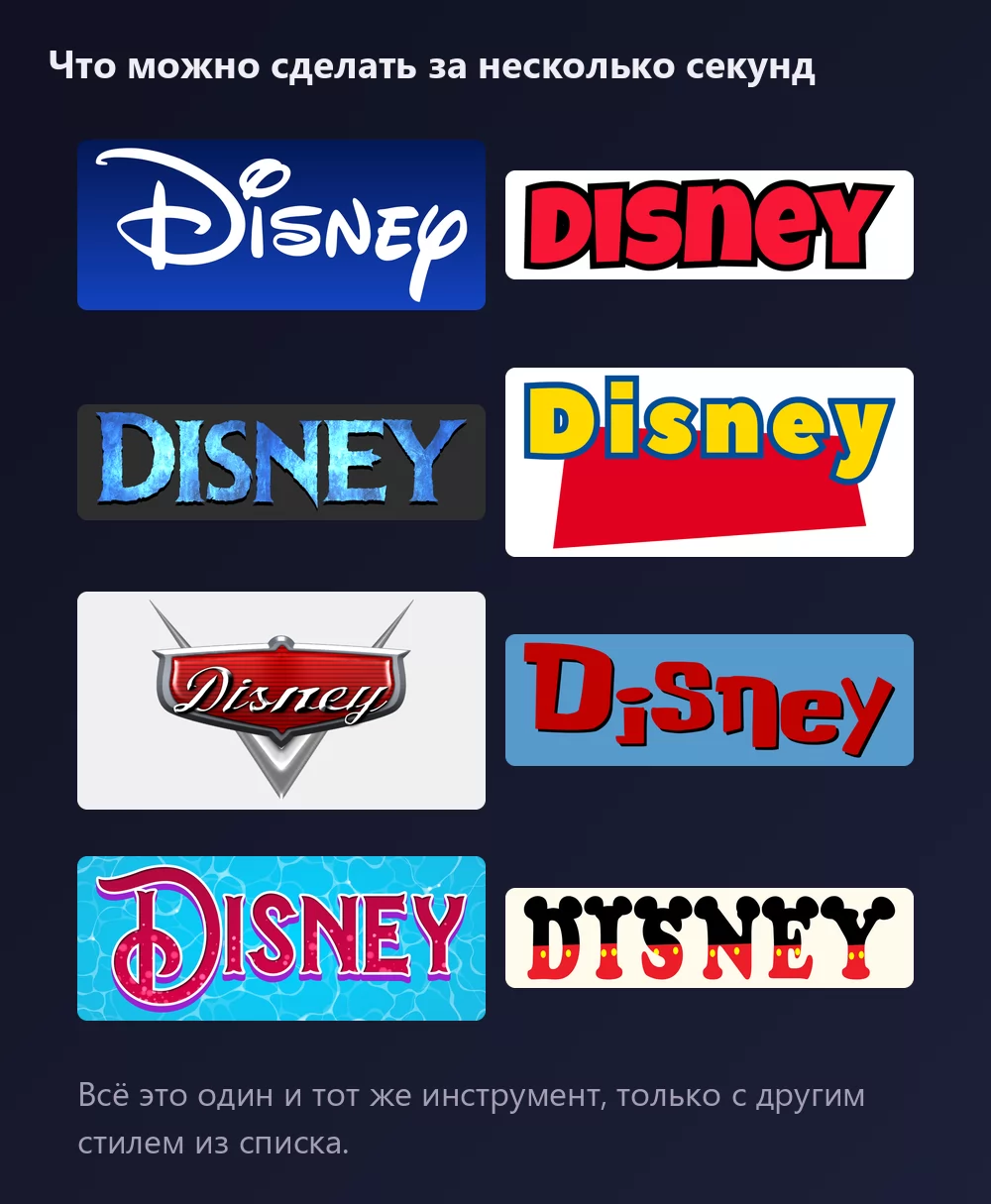
О шрифте Disney
Компания The Walt Disney Company была основана в 1923 году братьями Уолтом и Роем О. Диснеем и выросла в одну из крупнейших медиакомпаний мира. Микки Маус, её самый известный персонаж, является официальным талисманом.
Надпись в логотипе это стилизованная версия подписи Уолта Диснея. Она служит корпоративным логотипом с 1956 года и никогда не выпускалась как шрифт: официального файла для установки не существует. Вместо него все скачивают Waltograph, шрифт, который Джастин Каллаган нарисовал по образцу логотипа. У него две версии: Waltograph 42, с прописными и строчными буквами, несколькими лигатурами и альтернативными знаками, и Waltograph UI, одноразмерный вариант, сделанный так, чтобы оставаться читаемым в мелком кегле и на экране. Обе бесплатны для личного использования.
Как сделать текст в стиле Disney
Откройте генератор и замените пример своим текстом: имя ребёнка, название праздника, фамилия для футболки в поездку. Буквы перерисовываются прямо во время набора. Оставьте обычный регистр: стиль подписи это рукописный шрифт, и слово прописными теряет высокую петлю D, по которой узнают Disney.
Классика это белая подпись на ярко-синем градиенте. На вкладке «Стили» заливка, обводка и тень меняются отдельно, так что форму букв можно оставить, а цвета увести в другую сторону: золото на тёмно-синем для свадьбы, розовый для праздника принцесс.
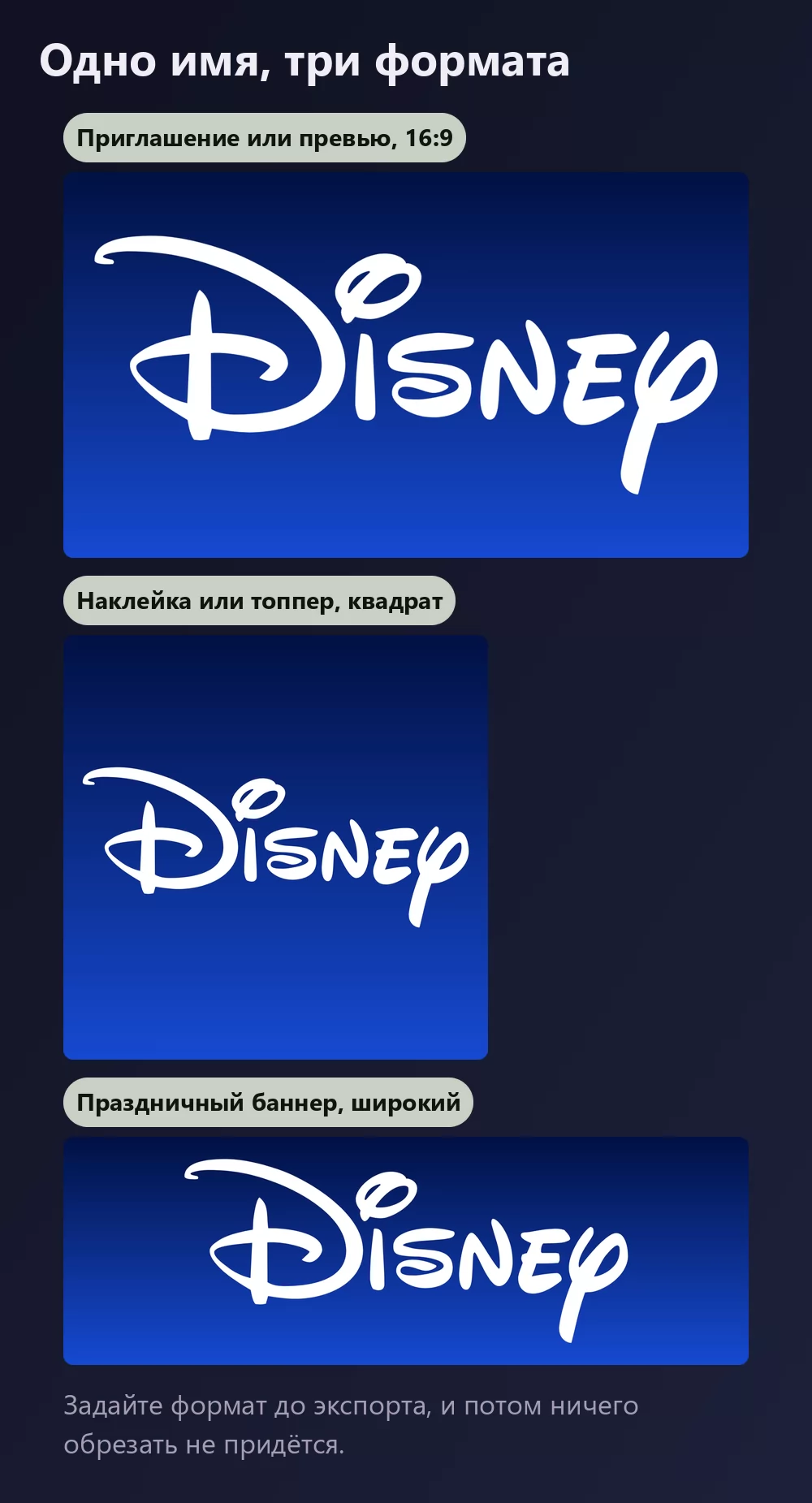
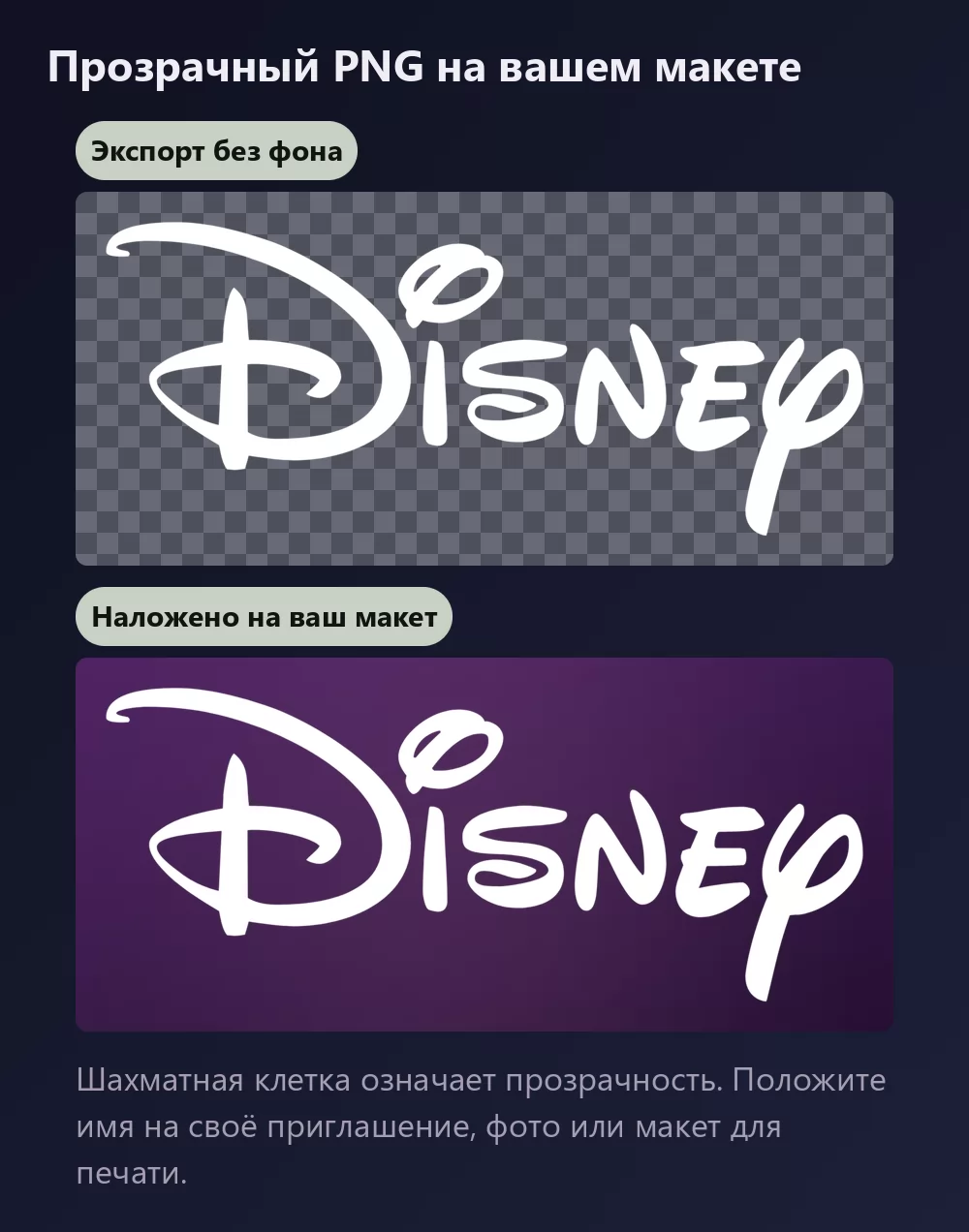
Длинные имена быстро заполняют ширину
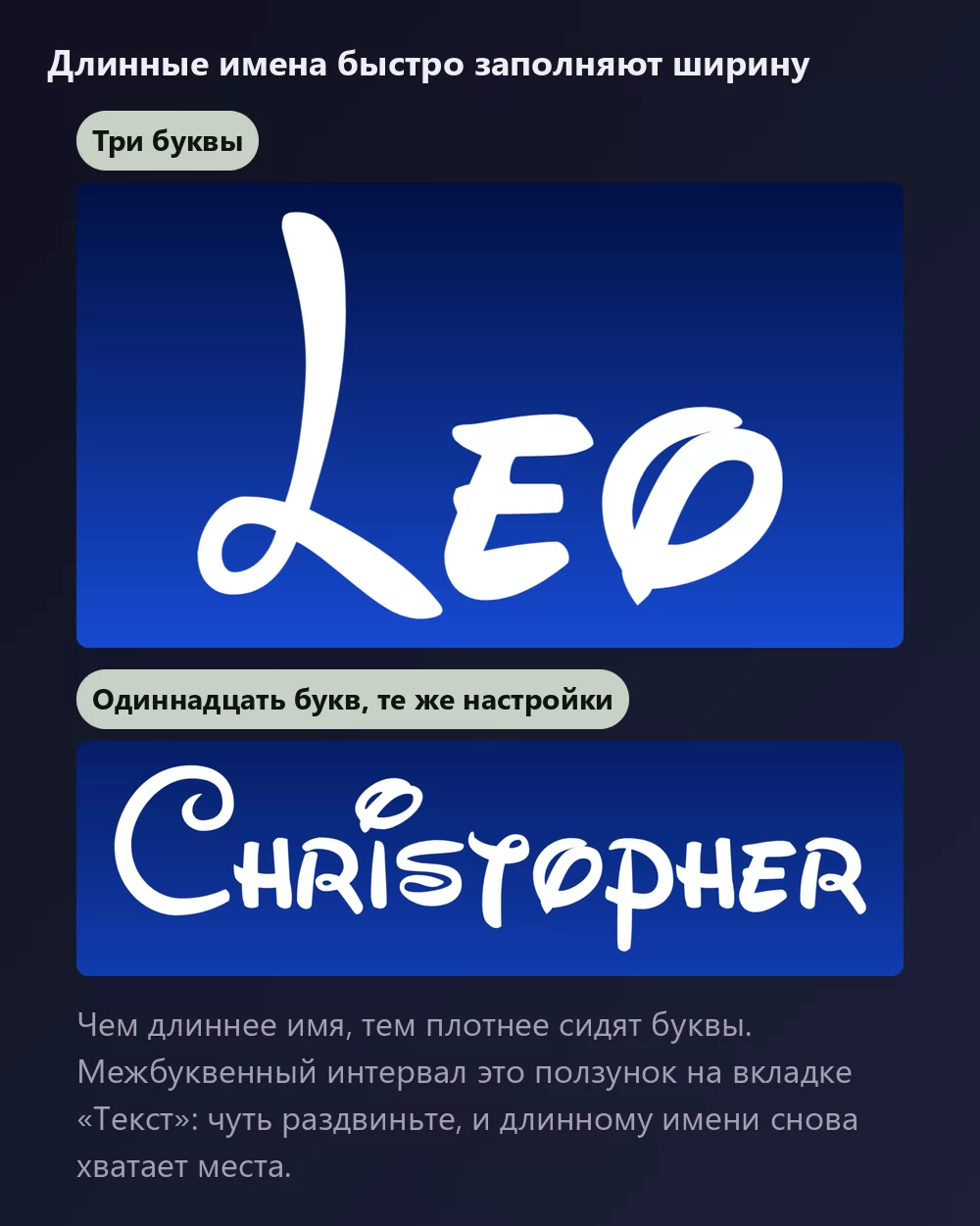
Чем больше букв, тем плотнее они сидят. Межбуквенный интервал это ползунок на вкладке «Текст»: чуть раздвиньте, и длинное имя перестанет выглядеть сжатым. На той же вкладке масштаб, межстрочный интервал, изгиб и поворот.
Стиль подписи или стиль Микки
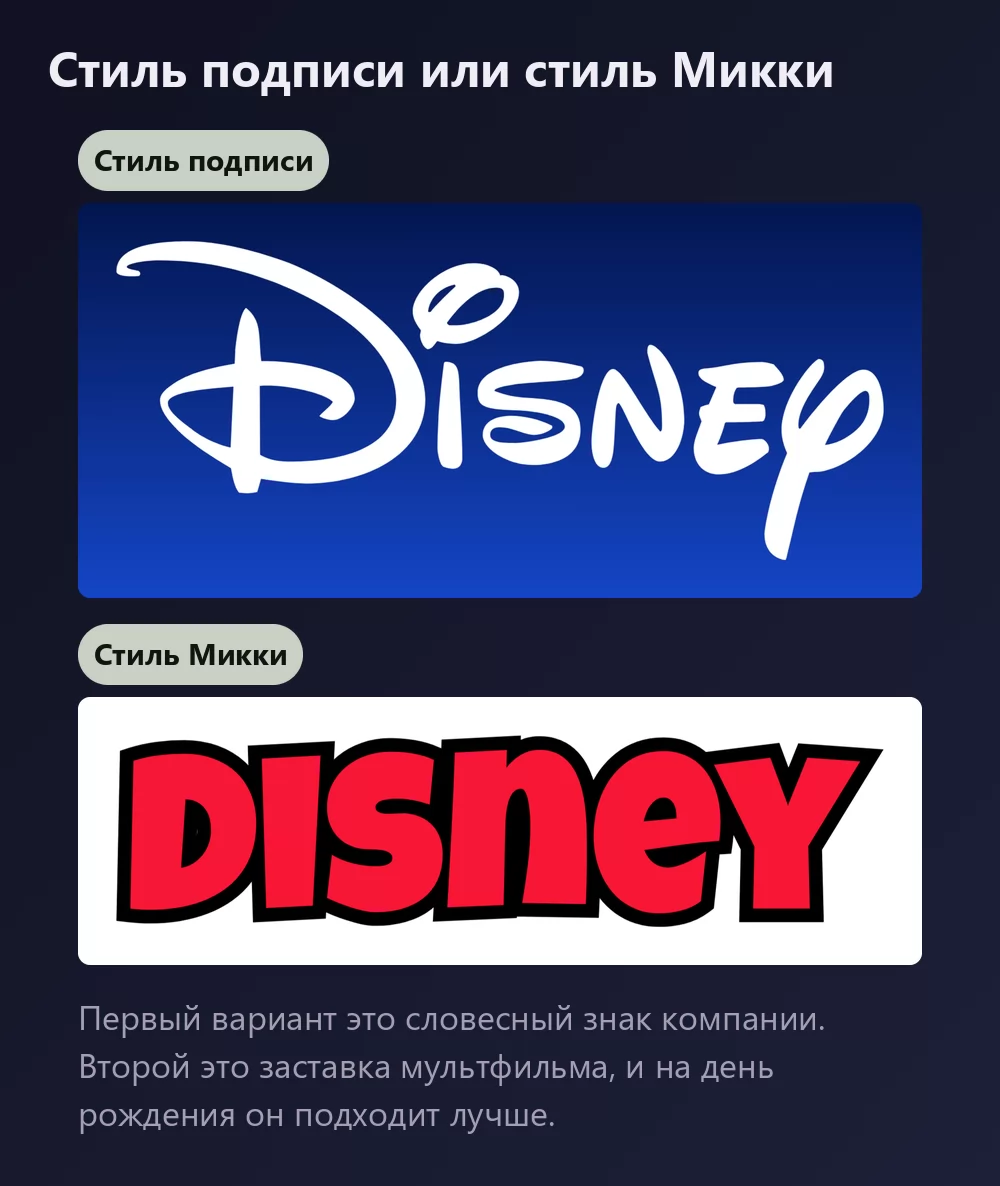
Стиль подписи это словесный знак компании: плавная рукописная надпись с высокой петлёй D, белым на синем. Именно это большинство представляет, говоря «шрифт Disney».
Стиль Микки это заставка мультфильма: жирные красные прописные с чёрной обводкой, надпись из короткометражек о Микки Маусе. В нём нет корпоративной символики, он читается с другого конца комнаты, и для первого дня рождения обычно подходит лучше подписи. В генераторе шрифта Микки Маус он есть как готовый стиль.
Какой шрифт, если вы хотите его установить
Сам логотип это не шрифт. Это леттеринг, нарисованный на заказ, поэтому любой файл с названием «шрифт Disney» является чьим-то воссозданием.
New Waltograph от 538Fonts это переработанная версия на FontSpace, где она самый скачиваемый шрифт в стиле Disney. FontSpace помечает её как полностью бесплатную, что на этом сайте включает коммерческое использование. Прочитайте readme внутри архива, прежде чем полагаться на неё в работе для клиента.
Mouse Memoirs от Astigmatic это выбор на случай, когда лицензия должна быть чистой. Он лежит на Google Fonts под Open Font License с 2012 года, а значит свободен для коммерческой работы. Это не копия подписи: высокий рукописный гротеск в духе ранних мультфильмов, который хорошо сочетается со стилем подписи на постере или в меню.
Шрифты Disney по фильмам и персонажам
Логотип компании это одно. У каждого фильма своя надпись в названии, и большинство результатов по запросу «шрифт Disney» на самом деле списки именно таких надписей. В том же генераторе есть стиль почти для каждой, каждый на своей странице:
- шрифт Микки Маус : жирные красные прописные с чёрной обводкой
- шрифт Минни Маус : розовый горошек и бантик на каждой букве
- шрифт «Холодное сердце» : ледяные голубые прописные с инеем по краям
- шрифт «История игрушек» : жёлтые буквы с синей обводкой на красном блоке, и у нас есть полный гид по «Истории игрушек»
- шрифт «Тачки» : хромированная эмблема с красной надписью, прямо с капота
- шрифт «Лило и Стич» : нарисованные от руки красные буквы на синем
- шрифт «Русалочка» : узорная фиолетовая антиква над водой
Нужно ли набирать прописными? Нет. Подпись это рукописный шрифт, и её характер идёт от высокой петли D и строчных букв. Прописные его теряют.